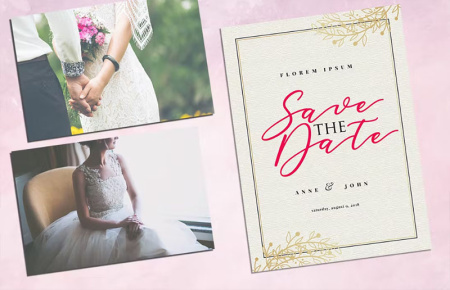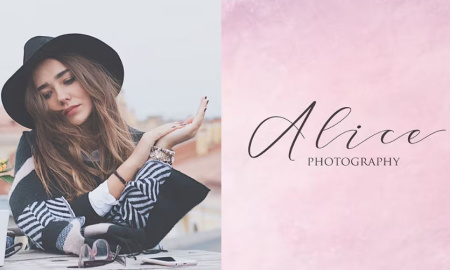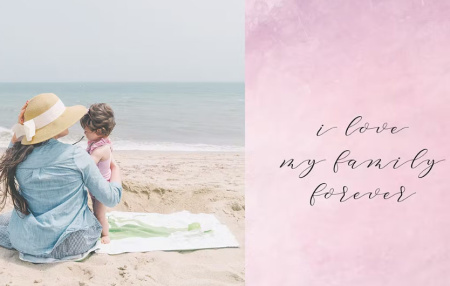
فونت انگلیسی زیبا Donita Script
فونت انگلیسی زیبا Donita Script یک فونت نرم و زیبا است که با قسمت بالای حرف ارتباط دارد. یک فونت بسیار زیبا، لوکس و جذاب است. این فونت برای تکمیل نیازهای طراحی شما در ساخت آثار شگفت انگیز است. مناسب برای برندسازی، دعوتنامه عروسی، مجلات، لیوان ها، کارت ویزیت، نقل قول ها، پوسترها و بسیاری موارد دیگر که می توانید در پروژه بزرگ خود استفاده کنید بسیار زیبا خواهد بود. برای مشاهده تصاویر این فونت زیبای انگلیسی از سایت gfx به ادامه مطلب مراجعه کنید.